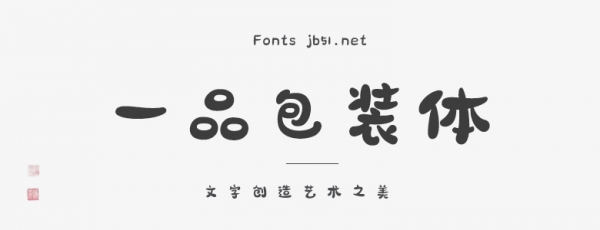
一品包裝體創(chuàng)作靈感來自于行書書法走勢,設(shè)計團隊取其部分精髓并結(jié)合當代設(shè)計師手法創(chuàng)作而成,專為包裝行業(yè)而設(shè)計。為此,字體的設(shè)計風(fēng)格“活潑、跳躍、手繪、圓潤、可愛、靈動”,排版風(fēng)格打破以往傳統(tǒng)手法,注重靈活機動性。正如名字所示“包裝體”,頭推的運用場景便是快消品包裝上,其次是作為標題運用。當然并不限制多方位運用,海報、標志、橫幅、等均可。歡迎喜歡此字體的朋友前來下載使用。